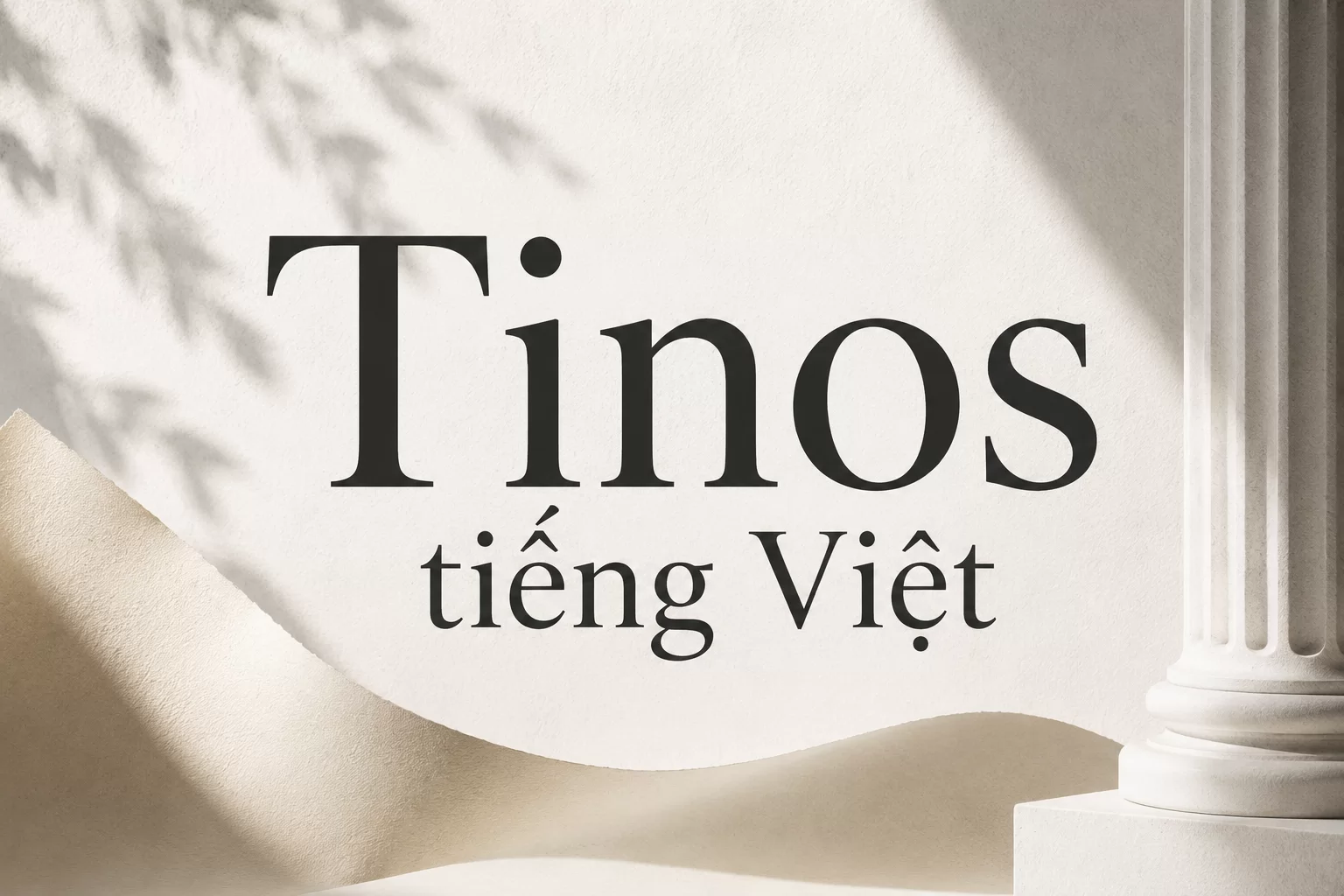
Tinos là phông chữ serif mang phong cách cổ điển, được thiết kế với khả năng hiển thị rõ ràng và cân đối trên cả màn hình lẫn bản in. Với các đường nét thanh lịch, khoảng cách ký tự hợp lý và độ dễ đọc cao, Tinos là lựa chọn phù hợp cho sách, báo, tài liệu, website, blog, luận văn và nhiều ấn phẩm có lượng văn bản lớn.
Bên cạnh việc tối ưu cho nội dung dài, Tinos cũng có thể sử dụng trong các thiết kế mang phong cách trang nhã, chuyên nghiệp như tạp chí, brochure, hồ sơ năng lực, thiệp mời hay nhận diện thương hiệu. Font hỗ trợ đầy đủ chữ tiếng Việt, giúp hiển thị dấu sắc nét và đồng nhất trên nhiều nền tảng.
Design: Steve Matteson